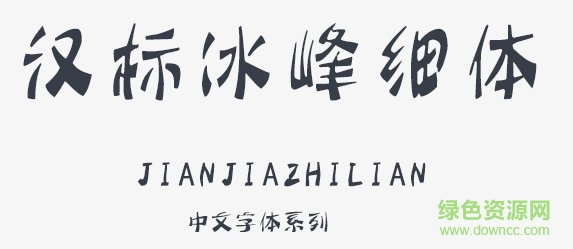
漢標(biāo)冰峰細(xì)體字體是一款造型上兼具藝術(shù)字體和卡通字體風(fēng)格的毛筆字體,干練Q萌的筆觸讓文字既大方端正也生動活潑,快來綠色資源網(wǎng)試試吧!
漢標(biāo)冰峰字體包括漢標(biāo)冰峰細(xì)體字體和漢標(biāo)冰峰粗體字體,整體風(fēng)格十分個性,字跡清晰而醒目,更用戶帶來絕佳的閱讀體驗!